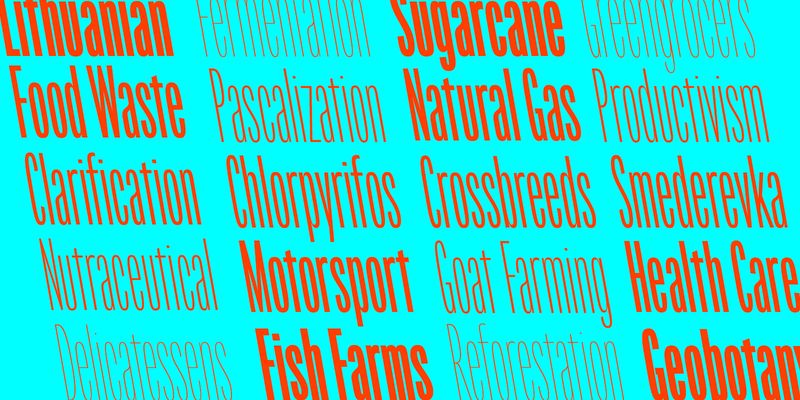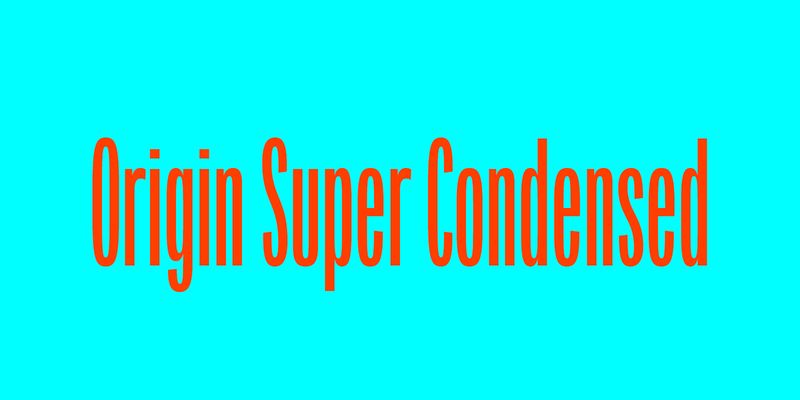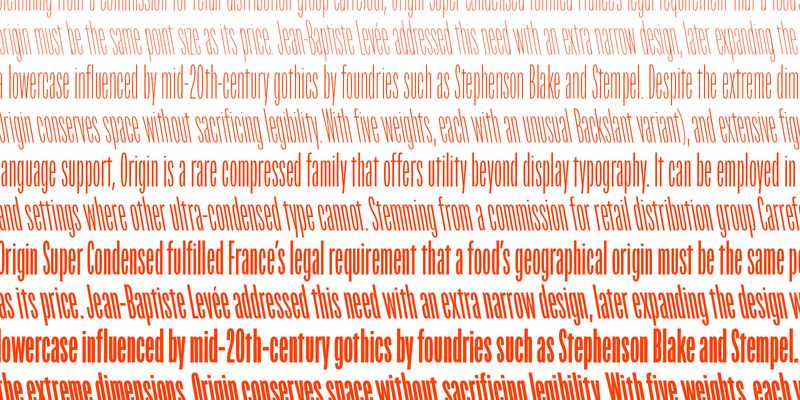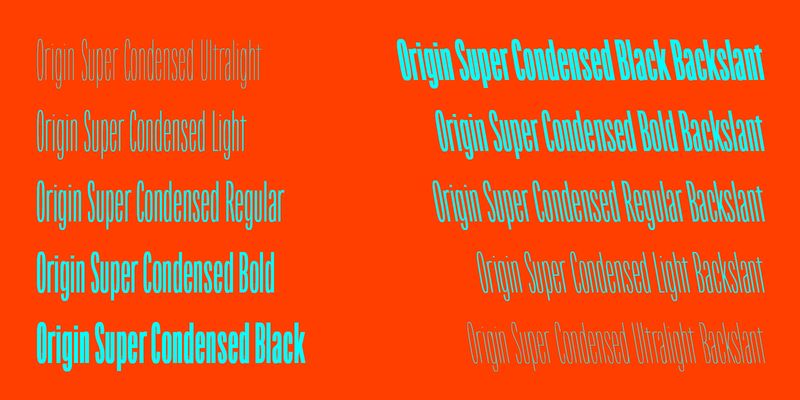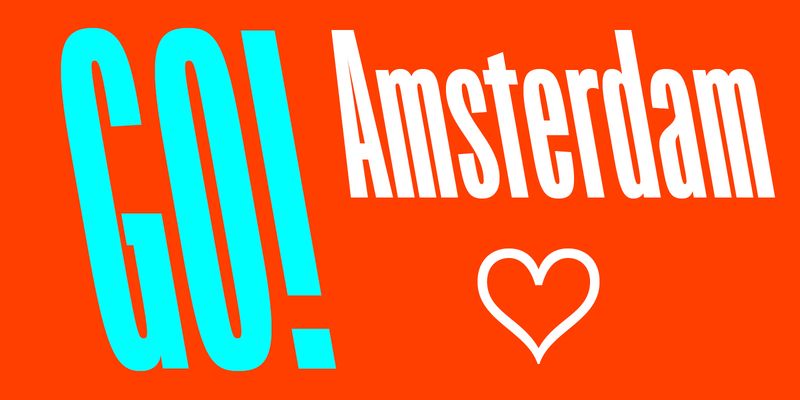
극단적인 크기에도 불구하고 Origin은 가독성을 희생하지 않으면서 공간을 절약합니다. 5가지 두께 설정(각각 특이한 Backslant 변형 포함)과 광범위한 숫자 및 언어를 지원하는 Origin은 디스플레이 타이포그라피 이상의 효용을 제공하는 보기 드문 압축 패밀리입니다.